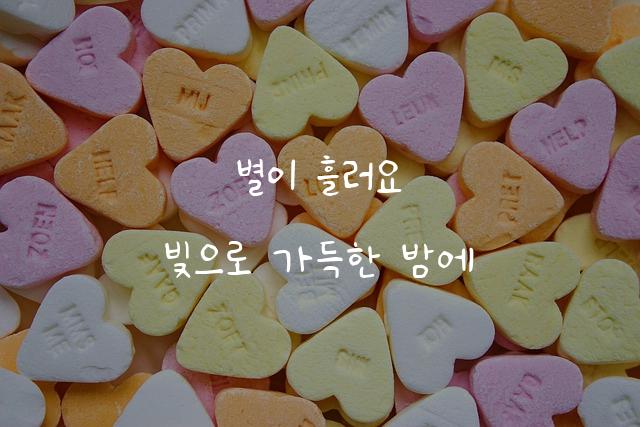
고서구체는 JellyBrick에서 제작한 한국어 폰트로, 삐뚤빼뚤하고 자유로운 감성이 특징인 서체입니다. 이 폰트는 전통적인 서예 스타일을 현대적인 감각으로 재해석하여 독특한 매력을 선사합니다.
고서구체은(는)
계열의 생김새를 가지고 있으며
출판 디자인, 초대장, 출판물 제목 등에서 자주 활용되며, 효과적인 메시지 전달에 적합합니다.
이 폰트는 출판/미디어, 문화/예술, 이벤트/웨딩 분야에 잘 어울리며,
신뢰감, 전통적, 클래식한 느낌을 담고 있는 것이 특징입니다.